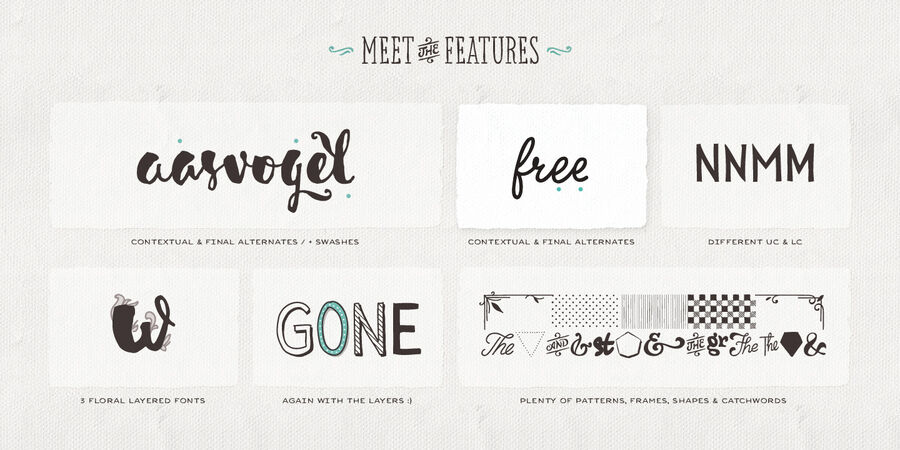
Шрифт Sensa – це сімейство шрифтів ручної роботи, що складається з 21 накреслення. Серед інших рукописних шрифтів цей поділяється на 6 підродин, кожна з яких вносить свій внесок у широкий діапазон настроїв – Sensa Brush, Sensa Pen, Sensa Wild, Sensa Sans, Sensa Serif та Sensa Goodies. Виберіть будь-який із шрифтів Sensa в якості провідного, а решта шрифтів можуть з легкістю супроводжувати його. Щоб працювати разом у всіх можливих комбінаціях, всі шрифти в цьому наборі створені з урахуванням цієї простої ідеї. Шрифт Sensa можна застосувати практично для будь-якого дизайнерського проекту – від реклами, упаковки, редакторських і брендингових робіт до веб, соцмереж та екранних проектів. Для краси та ніжних відчуттів або для більш чоловічого та сильного спілкування – у вас є широкий вибір. Гарнітура підтримує кирилицю. 2 шрифти Sensa доступні БЕЗКОШТОВНО. Функції OpenType: стилістичні альтернативи, контекстуальні альтернативи, розчерки, локалізовані форми. Шрифт розроблений командою Fontfabric в 2015-2018 роках.
Асоціації з сімейством шрифтів Sensa PenОсобистість і характер гарнітури:
святковий, ввічливий, красивий, радісний, щасливий, симпатичний, артистичний, милий, доброзичливий, крафтовий, смачний, добрий, М'який, рукотворний, ручний, домашній, затишний, довірчий, зелений, натуральний, природний, теплий, динамічний, рухливий, ламповий, апетитний, гнучкий, живий, оригінальний, привітний, свіжий, характерний, круглий, бадьорий, соковитий, стиглий, пустотливий, квітковий, виразний, приємний, літній, неформальний, емоційний, чуттєвий, колоритний, пластичний, ритмічний, округлий, якісний, сентиментальний, чесний, здоровий, грайливий, потішний, гладенький, кучерявий, весняний, ремісничий, сімейний, екологічний, прикольний, мотузковий, фермерський, гарненький, артізанальний, акуратний, побутовий